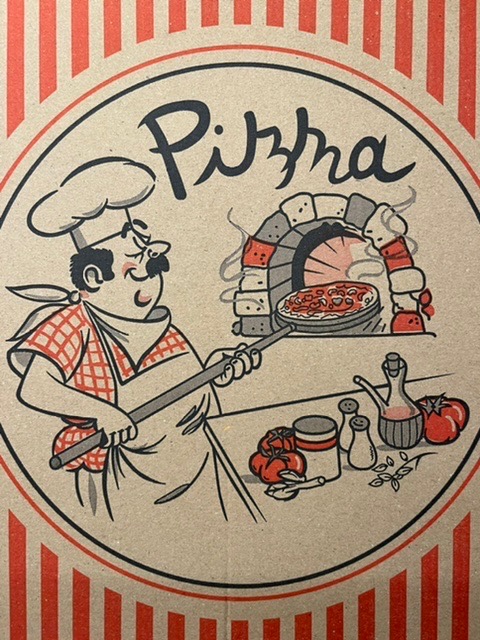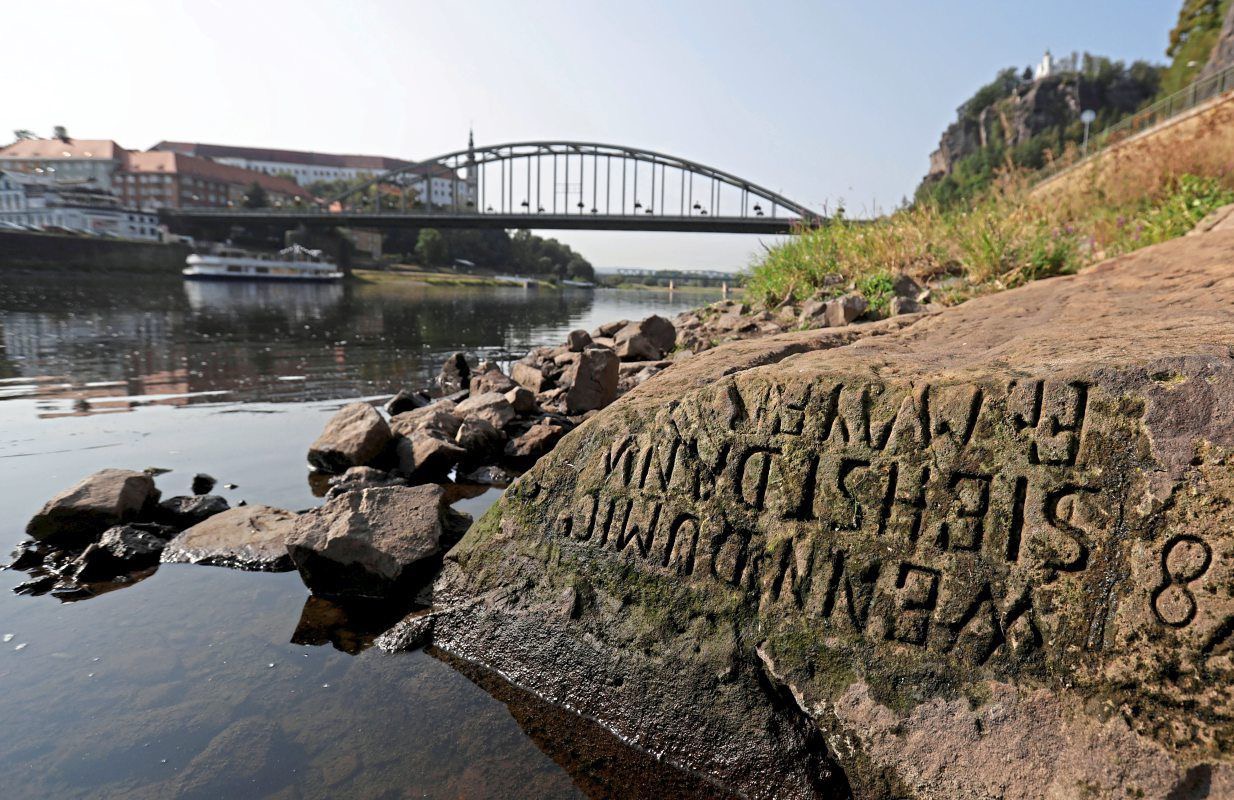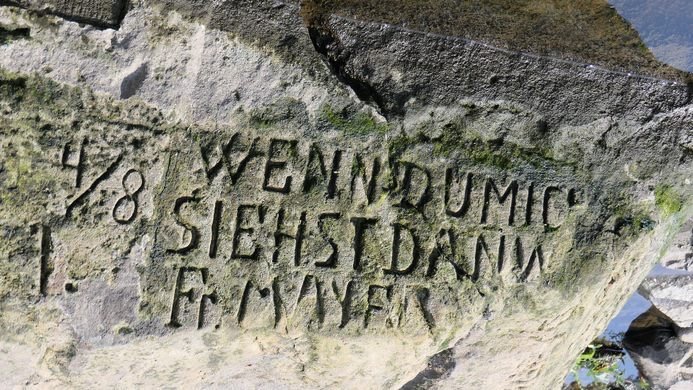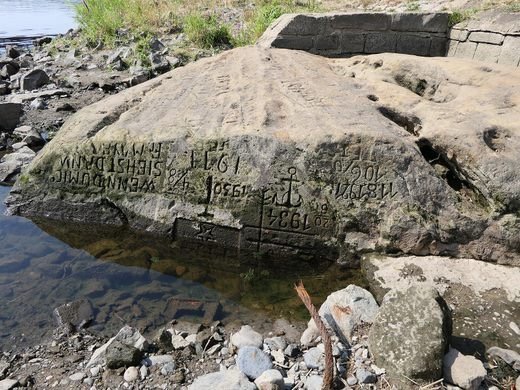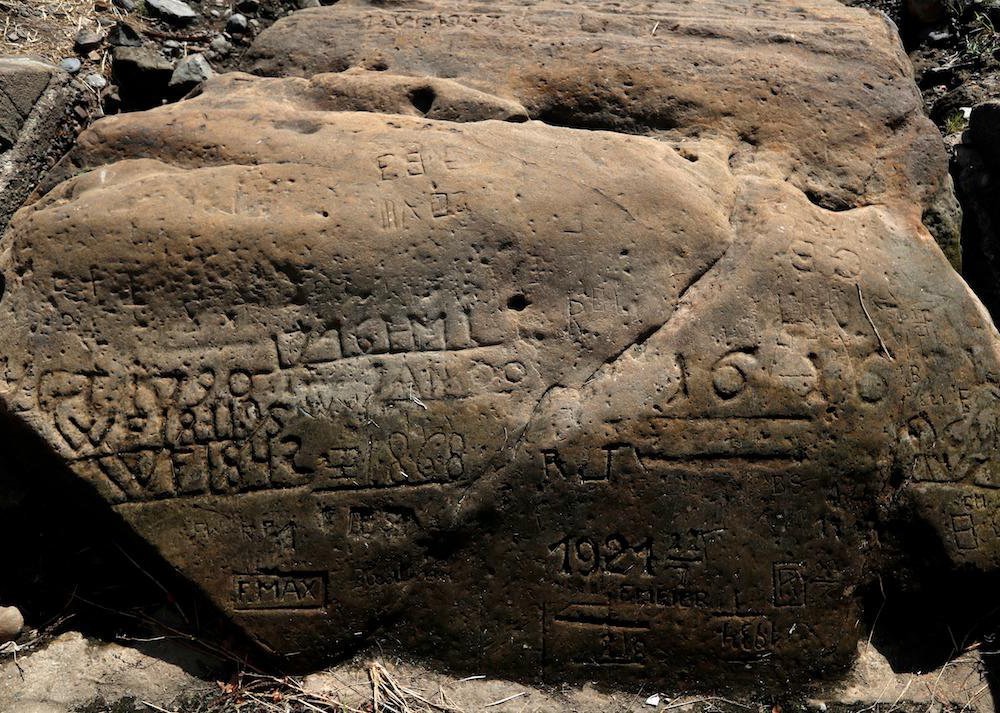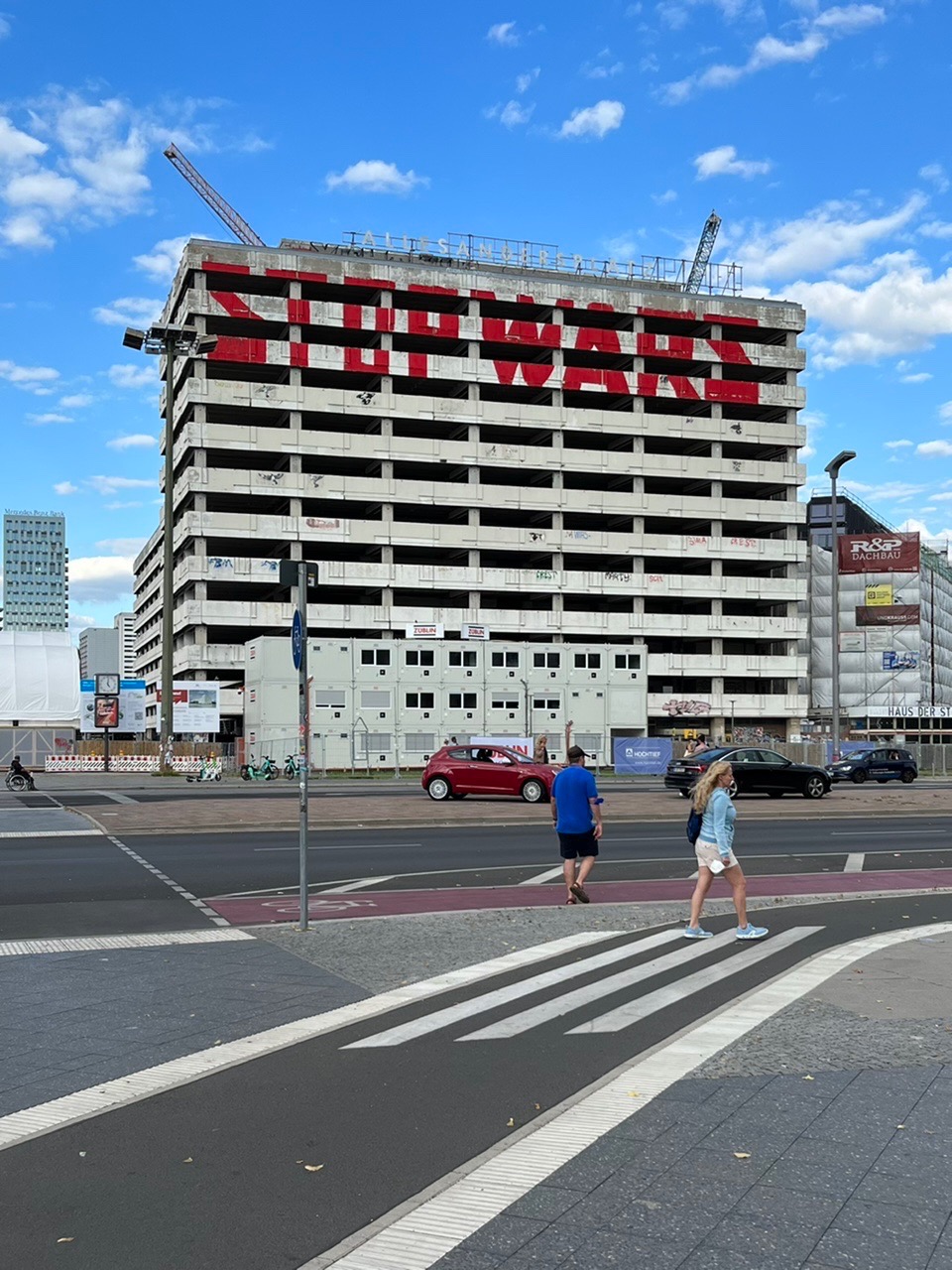
Hungerstein (Wasserpegelmarkierung) in der Elbe im tschechischen Děčín (Bild: 2018).
»Wenn du mich siehst dan w(eine)«
Fr. Mayer
Was mich wundert: Die Innschrift soll 1616 entstanden sein, zeigt aber eine Antiqua. Sie wurde im deutschsprachigen Raum aber erst im Laufe des 19. Jahrhunderts verstärkt genutzt … Überhaupt kommt mir auch die Ausdrucksweise für diese Zeit unpassend vor … Irgendetwas scheint hier nicht zu stimmen.
In dem Artikel steht, dass die älteste Inschrift aus dem Jahr 1616 ist, nicht aber, dass die von dir zitierte die älteste ist.
Diese Inschrift soll im 19. Jhd. entstanden sein, andere ab dem 15. Jhd.
Vielen Dank, inzwischen bin ich auch schlauer … Die Datierung 1616 wurde auf Twitter fälschlicherweise zum Ausgangsbild gepostet.
Hier die richtige Inschrift aus dem Jahre 1616 (u.a.):
Edit: Inschrift, nicht Stein.
Das Ausgangsbild ist anscheinend aus dem Jahr 1911 (1914?), kommt mir wie gesagt trotzdem irgendwie seltsam vor … War damals dieses IKEA-Geduze schon üblich?
Das a hat etwas diabolisches und die Buchstaben davor fletschen schon einmal die Zähne.
Und die Salz- und Pfefferstreuer wissen auch nicht so recht, was das sein soll.
Berlin, Haus der Statistik
Das besagte Haus soll übrigens einen neuen Schriftzug auf dem Dach bekommen. Vorschläge konnten bis 15. Juni über die Website des Hauses eingereicht werden. Die Schrift steht bereist fest.
Der Schriftzug ist bereits mit dem Landesdenkmalamt abgestimmt. Hieraus ergeben sich die maximale Schrifthöhe von 1,5m und die Schriftart »Bank Gothic«. Die Buchstaben werden so produziert, dass sie nachts leuchten. Insgesamt darf der Schriftzug nicht länger als 46 m sein, woraus sich eine maximale Zeichenzahl von 22 Buchstaben ergibt!